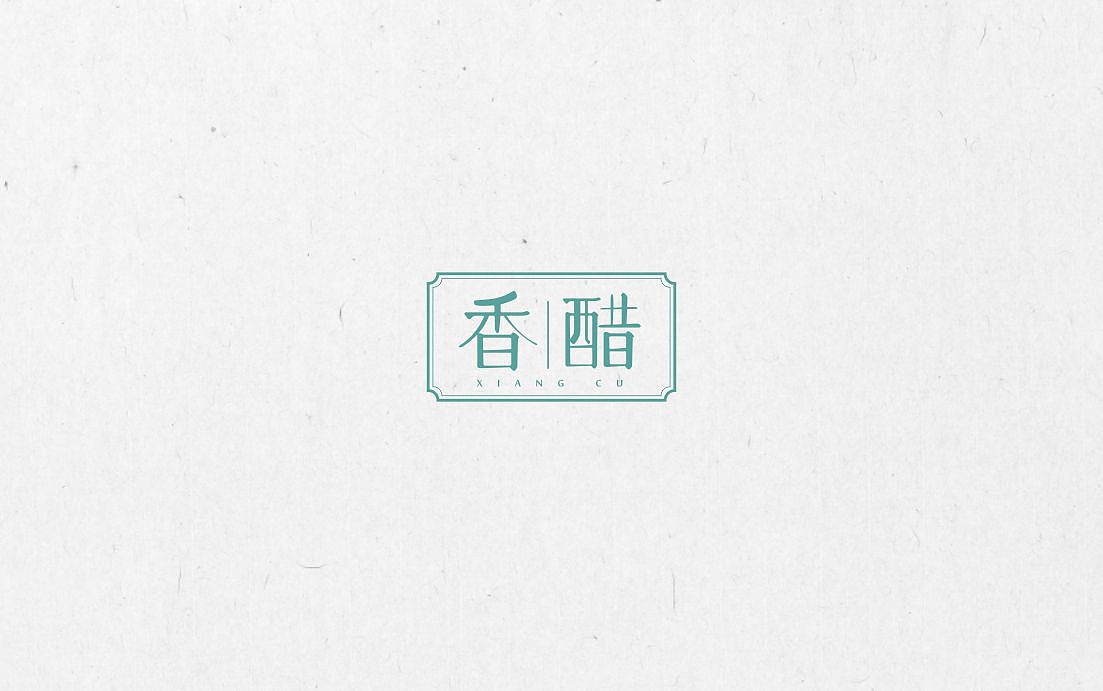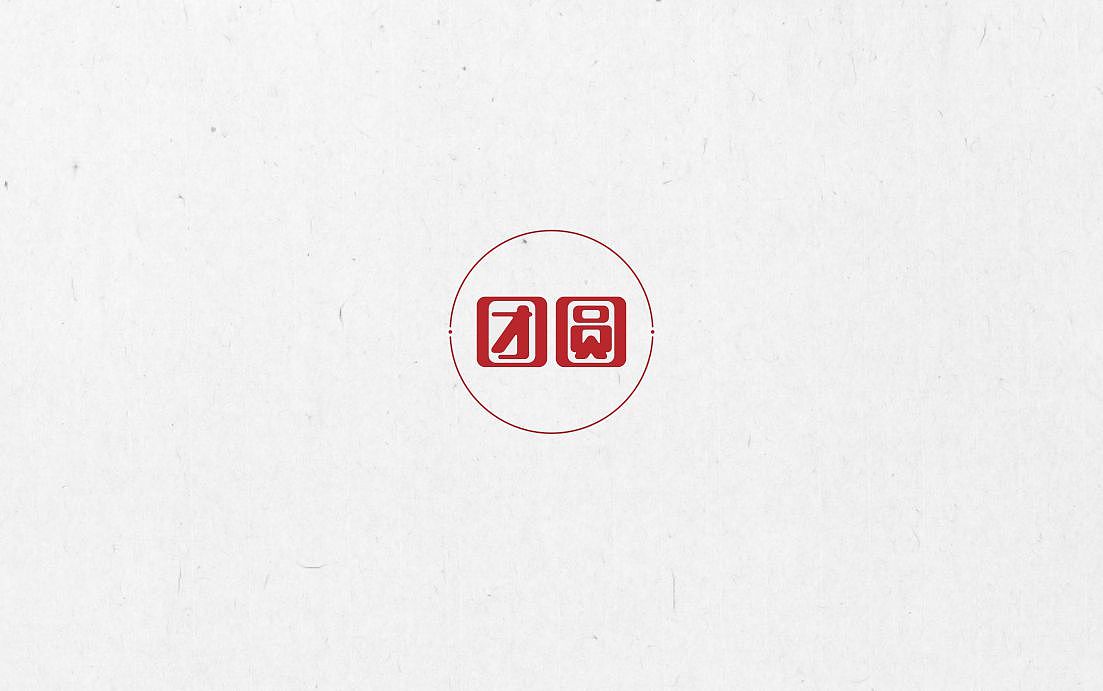
前期字体练习
由于平时工作事情繁杂,与字体接触甚少,没有天分,又不够努力。这里整理里前期的字体练习,希望得到交流和指点,哪里不好就直接喷吧。
前期字体作业练习。
夏天快来了。什么?夏天还没来?那怎么满大街穿裙子了?
前期字体设计练习。
设计回归,没有笔画线条,只剩图形色块了……
我像路人看着你走,逃到爱情外的你终于罢休。
想要有个家,一个不需要多大的地方。
疯狂的楼市,牵动着房租的上涨,咋就不见工资涨呢???
前期字体作业练习(二)
前期字体作业练习(三)
你的坚持,终将美好——无腿登山者,陈州
前期字体作业练习(四)